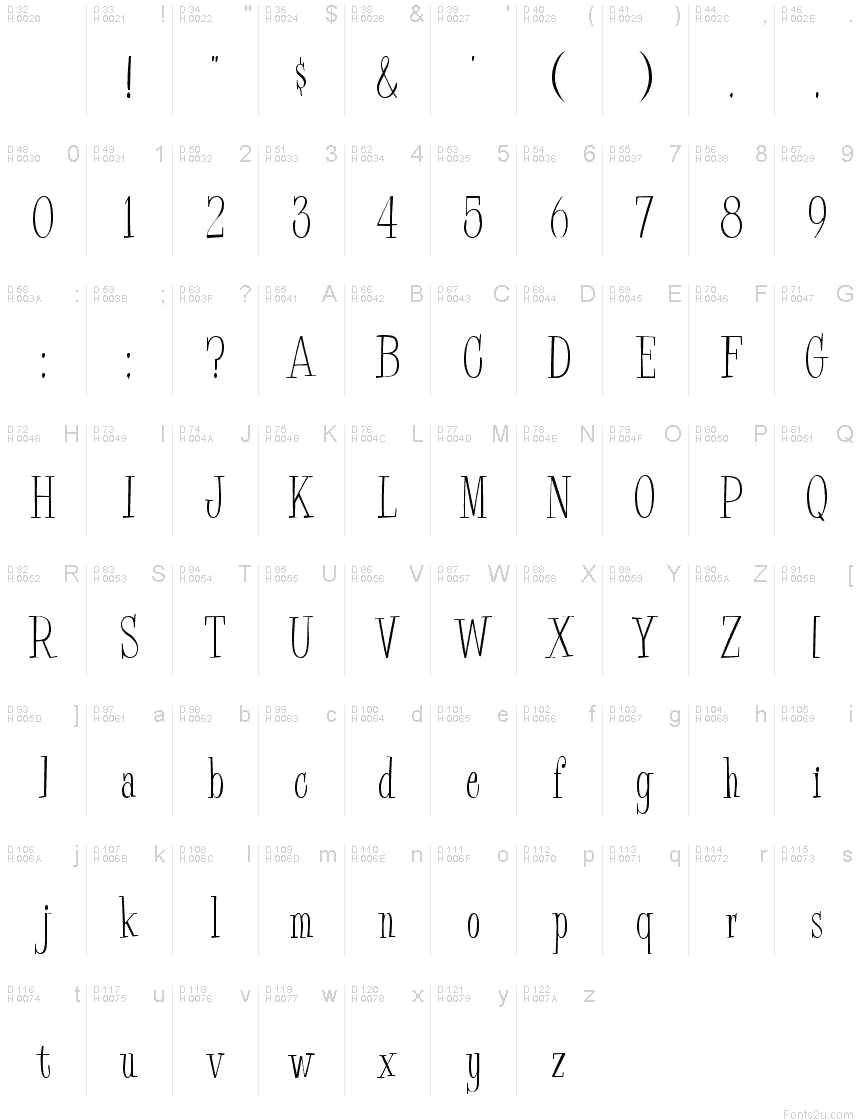
Bud Easy autorstwa Johna D. Banksa to darmowy krój pisma typu comic serif o cudownie nietuzinkowym uroku. Litery są wysokie, smukłe i lekko kołyszące się, niczym linie tuszu nakreślone szybko pewną ręką. Te oszczędne, eleganckie pociągnięcia i luźne, pochylone kształty nadają mu swobodny charakter, który pozostaje czytelny, wnosząc lekko figlarny ton do każdego nagłówka czy krótkiego hasła.
Bud Easy błyszczy na okładkach książek, niezależnych zinach, plakatach, pomysłowych opakowaniach, kartkach okolicznościowych i grafikach w mediach społecznościowych – wszędzie tam, gdzie potrzebujesz dowcipu bez zbędnego chaosu. Wąskie formy sprawiają, że długie tytuły dobrze się mieszczą, a niezobowiązujące krzywizny zapewniają przyjazny, a nie sztywny wygląd. Dla zachowania równowagi połącz Bud Easy z prostym, bezszeryfowym krojem o niskim kontraście w tekście głównym i pozwól temu fontowi przejąć stery w najbardziej wyrazistych momentach.